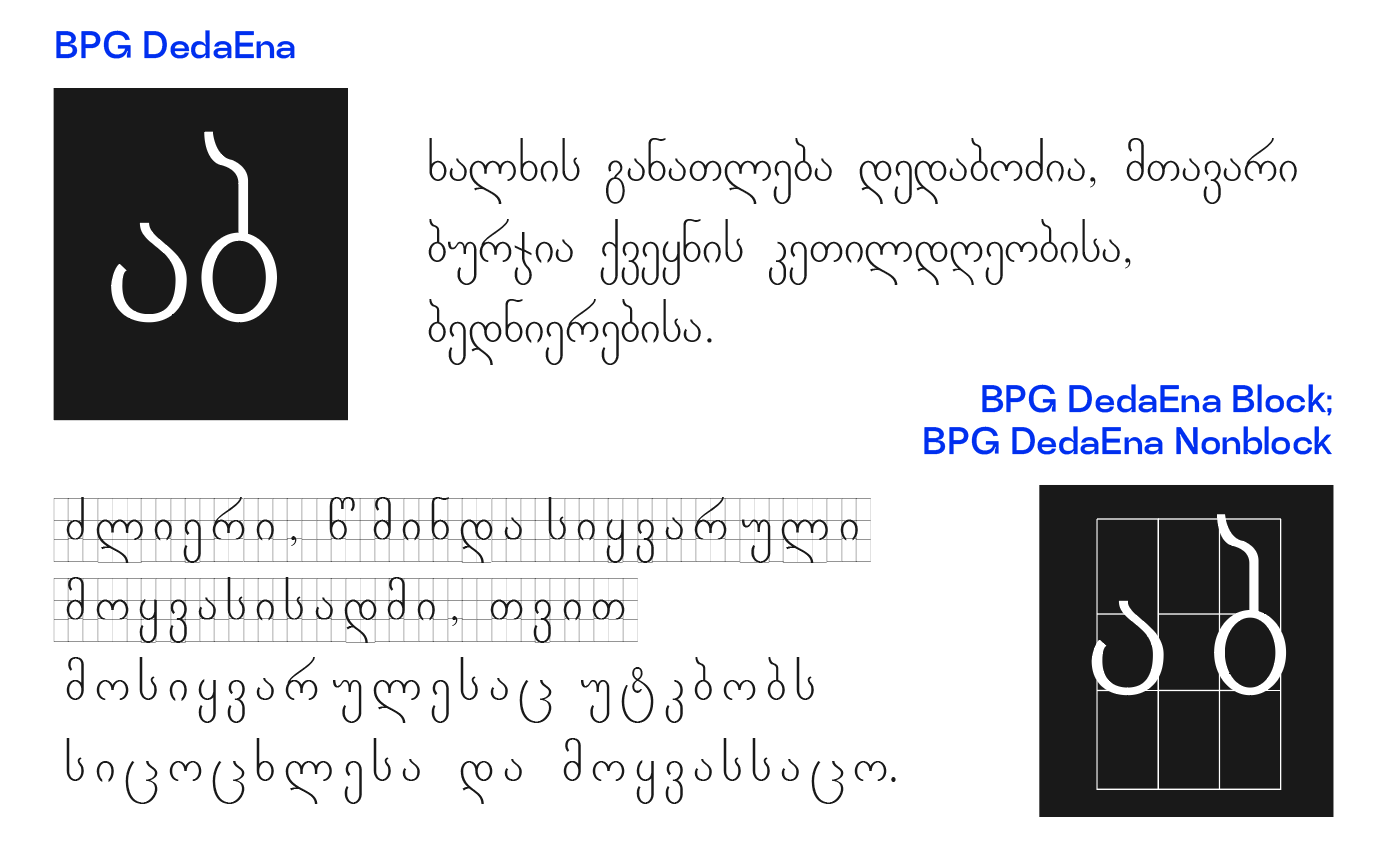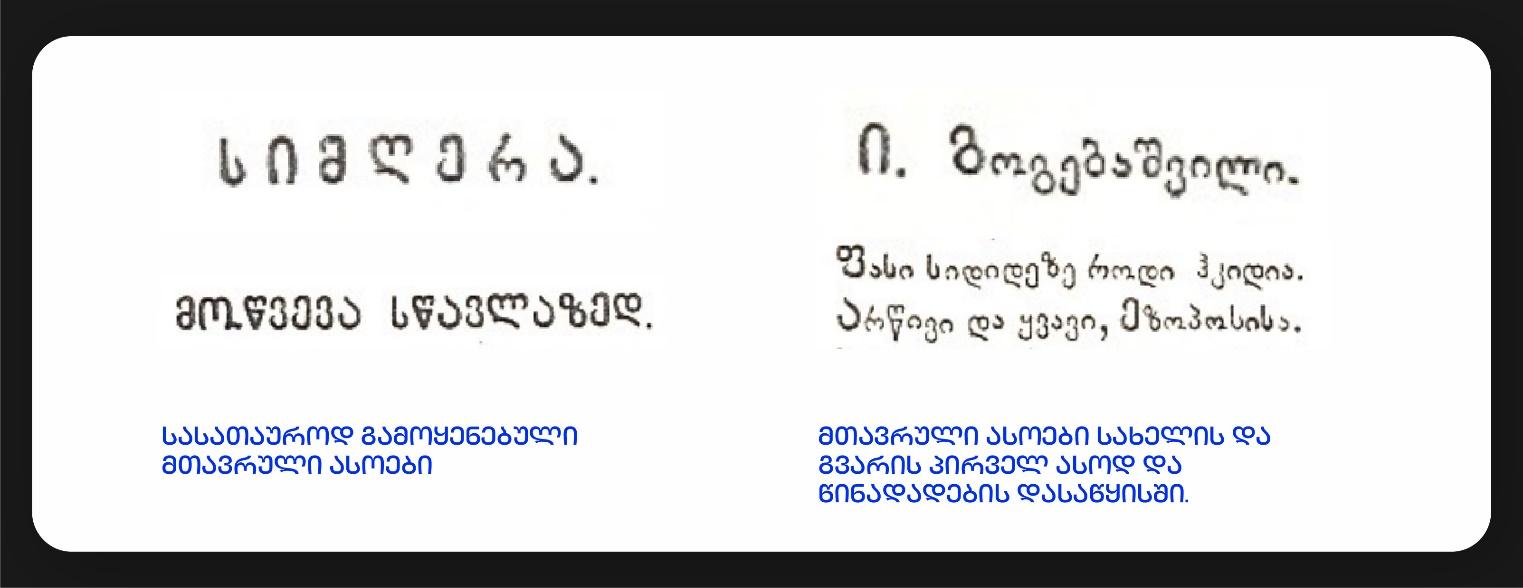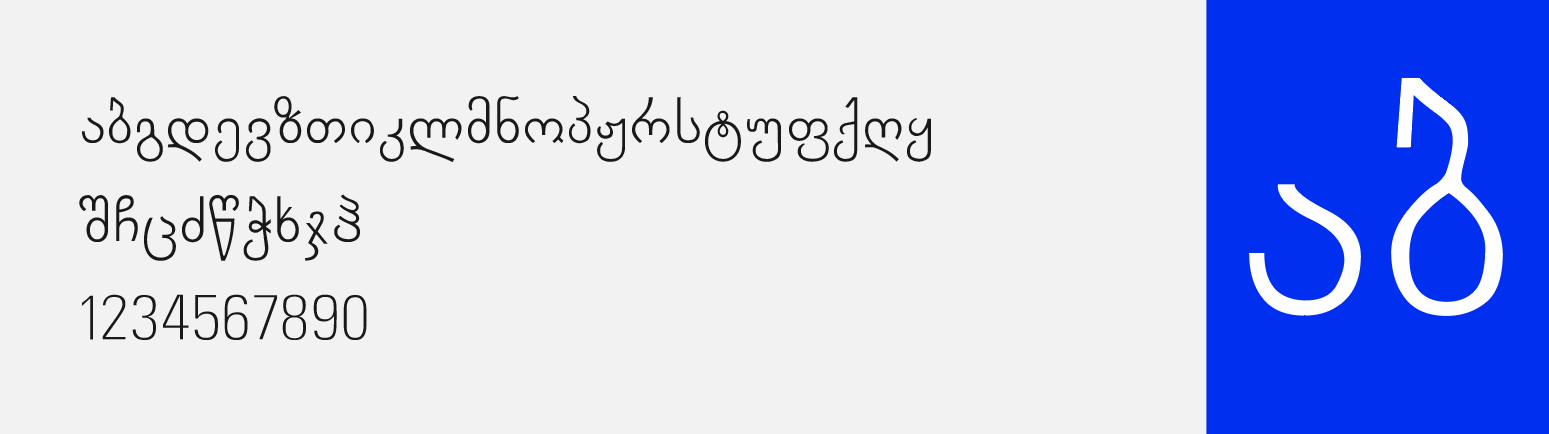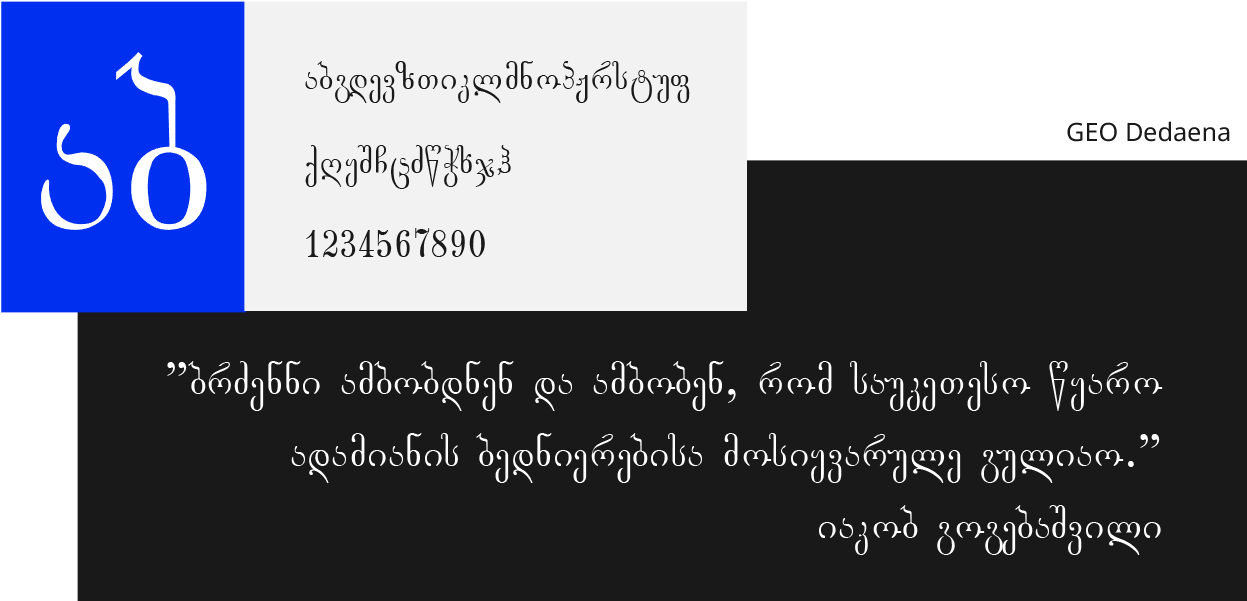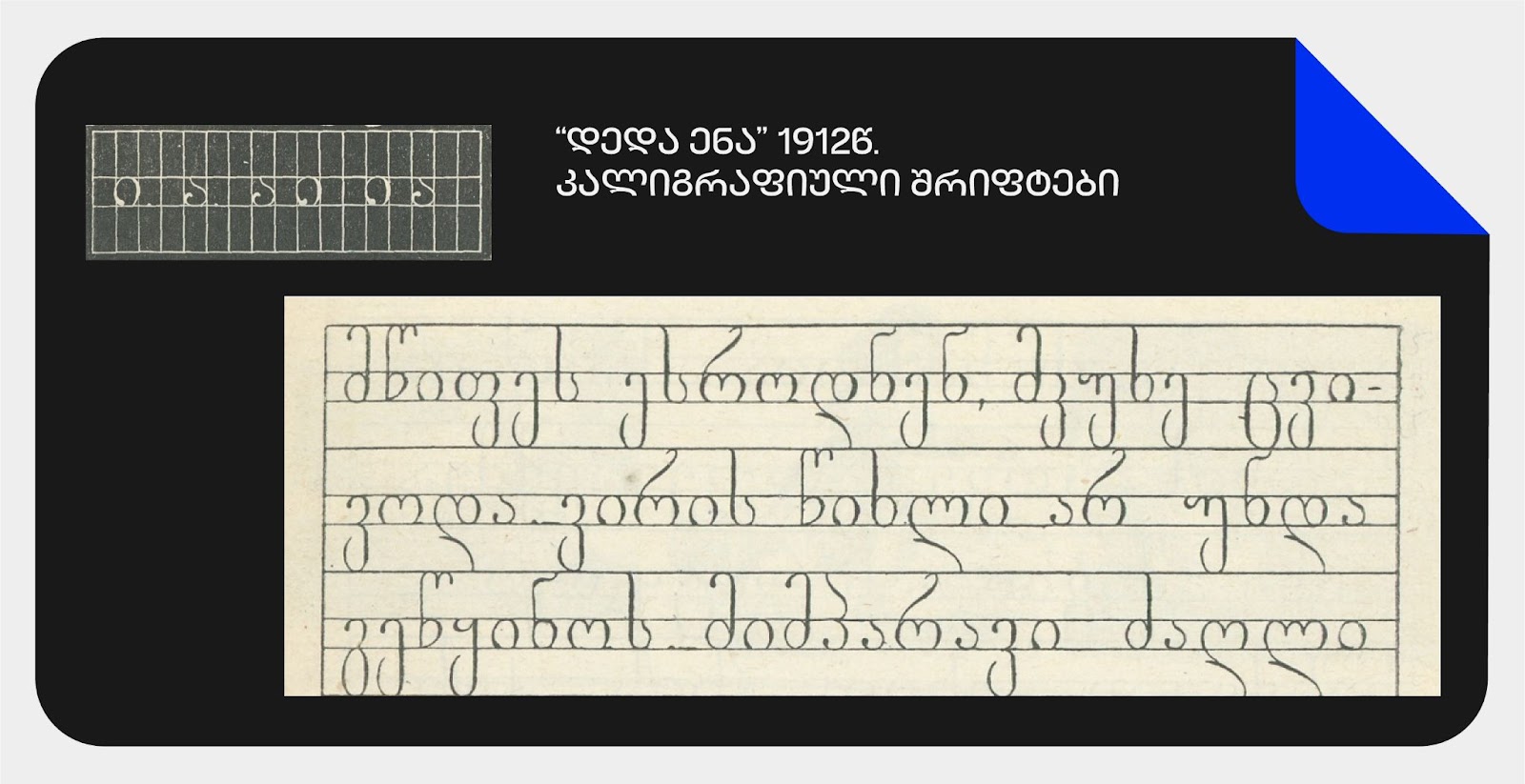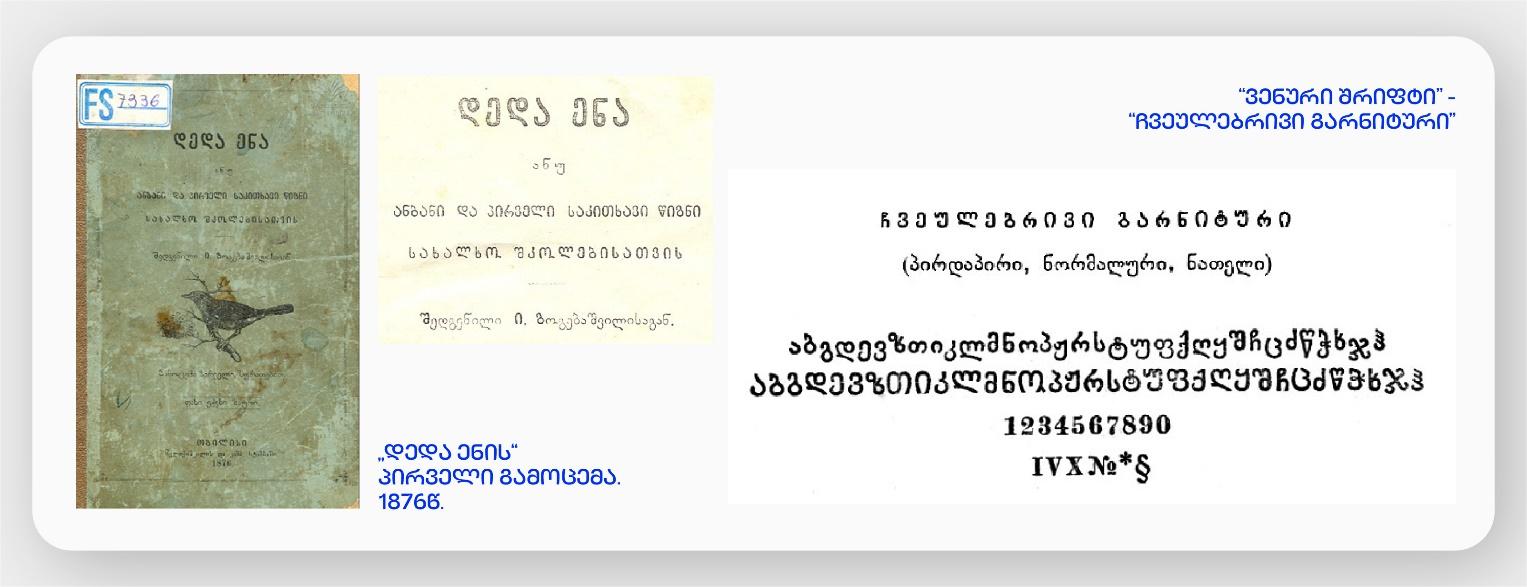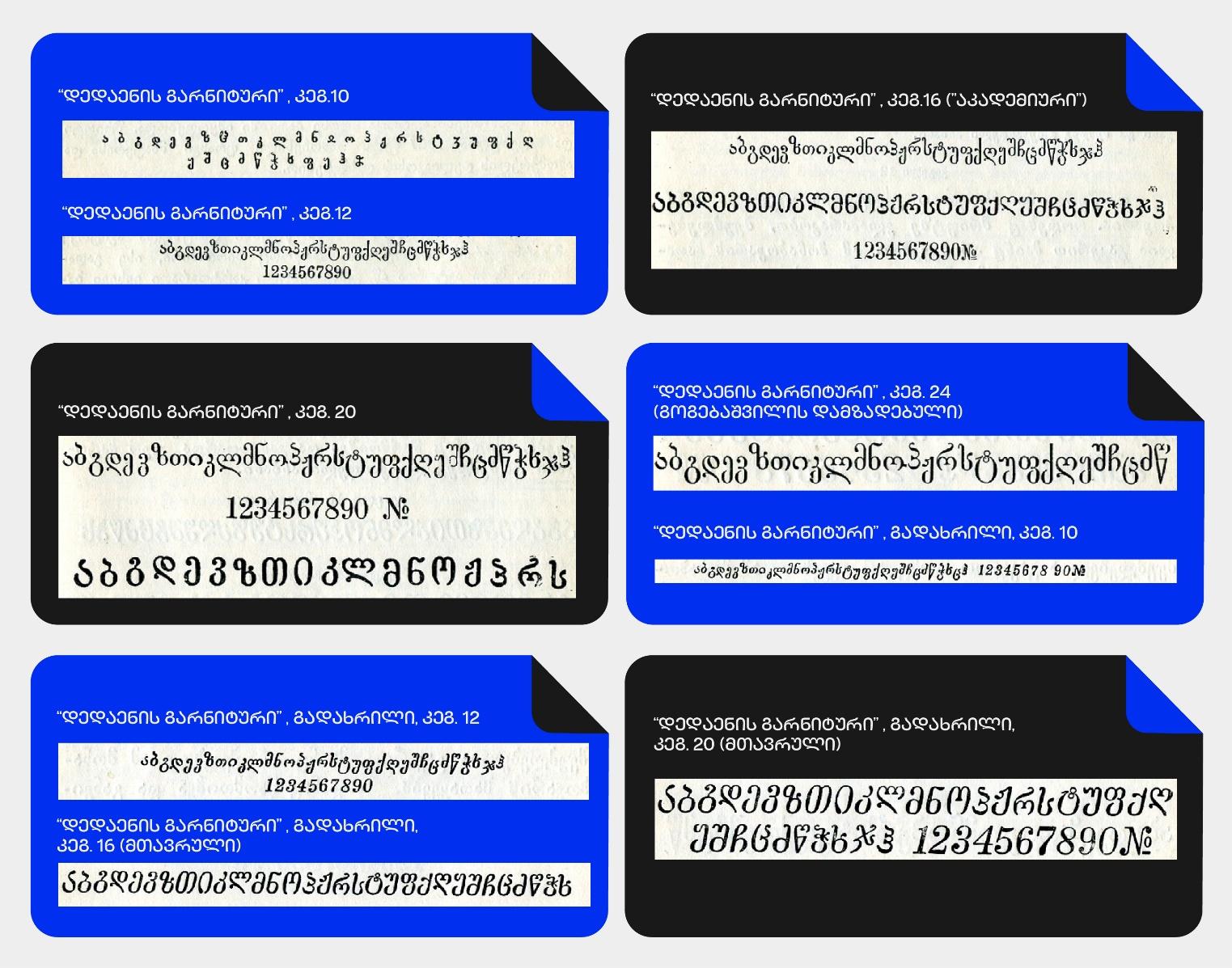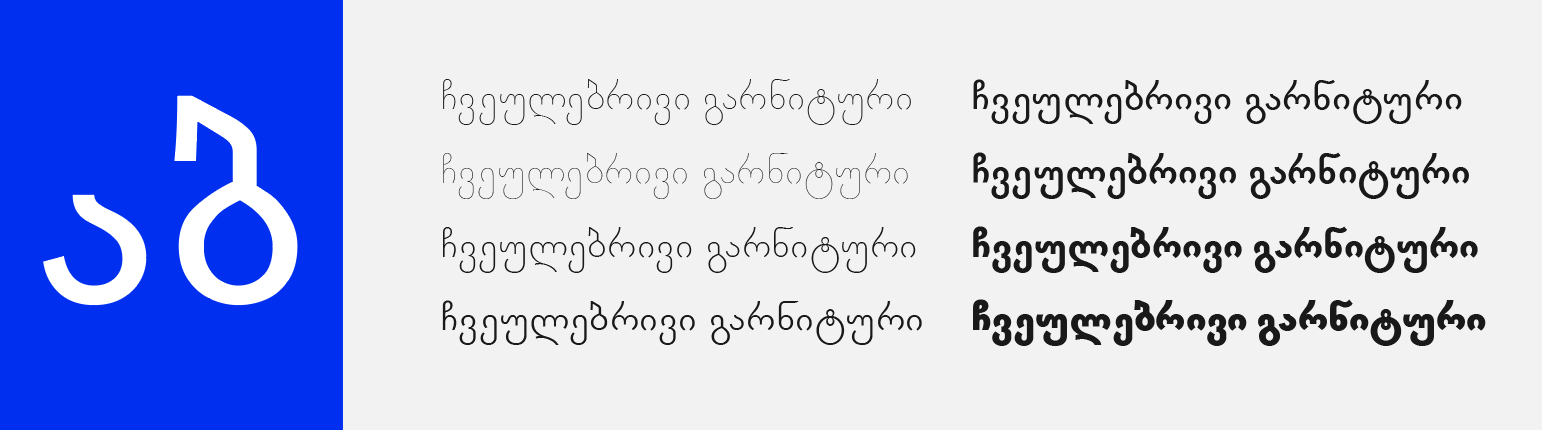
პირველი „დედა ენა“ დაიბეჭდა 1876 წელს, მელიქიშვილის სტამბაში. იმ დროისთვის სასტამბო მეურნეობა შრიფტების მრავალფეროვნებით ნამდვილად არ გამოირჩეოდა.
პეტერბურგიდან საქართველოში დაბრუნებულმა ახალგაზრდობამ ძალიან კარგად იცოდა, რამდენად მნიშვნელოვანი იყო სასტამბო საქმის გამართვა. თბილისის სტამბებში მხოლოდ პეტერბურგის აკადემიის მოძველებული და გაცვეთილი ქართული შრიფტები მოიპოვებოდა. 1863 წელს შეიკრიბა რამოდენიმე ახალგაზრდა და დააარსეს სტამბა. ესენი იყვნენ: სტეფანე მელიქიშვილი, დიმიტრი ბაქრაძე, ვახტანგ თულაშვილი და ნიკოლოზ ღოღობერიძე.
კონკურსის დახმარებით შეირჩა მიხეილ ყიფიანის შრიფტის ესკიზი. 1864წ. სტეფანე მელიქიშვილი გაემგზავრა ვენაში შრიფტის ასოების შესაკვეთად. დამზადდა ახალი მხედრული შრიფტი „ვენური“ (შემდგომში „ჩვეულებრივი გარნიტური“ ეწოდა), რომელიც ახალ ფურცელს წარმოადგენდა ქართულ ტიპოგრაფიაში: ეს იყო პირდაპირი მოხაზულობის, მარტივად საკითხავი შრიფტი, რომელმაც ქართული შრიფტი პირველად გაათავისუფლა ხელნაწერის გავლენისგან.
გოგებაშვილს შრიფტების დიდი არჩევანი არ ჰქონია, როცა „დედა ენის“ პირველ გამოცემაზე მუშაობდა. ის „ვენური“ შრიფტის მიმართ დადებითად იყო განწყობილი, „კარგ, მრგვალ და გარკვეულ შრიფტად“ მიაჩნდა. თავის სახელმძღვანელოშიც პირველად სწორედ „ვენური“ გამოიყენა.
აღსანიშნავია, რომ ამ შრიფტს ახლდა მთავრული ასოებიც. ეს იყო პირველი შემთხვევა, როცა მხედრულის მთავრული ხმარებაში შემოვიდა. „დედა ენაში“ ორი ფუნქციით გამოიყენებოდა:
დღეს მთავრულს მხოლოდ პირველი ფუნქციით ვიყენებთ, ლათინურის იმიტაციამ ქართულ ენაში ფეხი ვერ მოიკიდა.
მიუხედავად იმისა, რომ სასტამბო შრიფტებიდან გოგებაშვილს ყველაზე მეტად „ვენური“ მოსწონდა, „დედა ენის“ პირველმა გამოცემამ მაინც დაიმსახურა კრიტიკა შრიფტის მცირე ზომის გამო, რაზეც იაკობმა გაზეთ „ივერიაში“ (1881წ. № 6, გვ. 163-4) გამოაქვეყნა პასუხი:
„ანბანი, მართალია, უფრო მომსხო ასოებით უნდა იყოს დაბეჭდილი, მაგრამ ეს ნაკლოვანება ჩვენი ბრალი კი არ არის, შრიფტების სიღარიბეზეა დამოკიდებული. ხეირიანი მსხვილი შრიფტი სრულიად არ მოიპოვება ჩვენებურს სტამბებში.“
„აკადემიურ“ შრიფტზე კი, რომლისგანაც შემდგომში დამზადდა „დედაენის გარნიტური“, წერდა:
„აკადემიის ასოებში იპოება მომსხო მეთექვსმეტე ნომრის შრიფტი, მაგრამ ესეც მეტად უშნო და ტლანქია, და გარდა ამისა არ უდგება სრულიად მელიქიშვილის ჩვეულებრივს შრიფტსა, რომელიც უფრო კარგს, მრგვალ და გარკვეულ შრიფტად მიგვაჩნია.”
როგორც ვხედავთ, გოგებაშვილს შრიფტების სიმცირის გამო სხვა გზა არ ჰქონდა, იძულებული იყო თავისივე დაწუნებული „აკადემიური“ აერჩია.
„აკადემიური“ პარიზში დამზადებული შრიფტი იყო პეტერბურგის სამეცნიერო აკადემიისთვის, რომელსაც თბილისის სტამბებში „ვენურის“ დამზადებამდე აქტიურად იყენებდნენ.
გოგებაშვილმა „აკადემიურის“ კეგლი 16 გაადიდებინა და ჩამოასხმევინა კეგ.24. ამ ორი ზომის შრიფტს დაერქვა „გოგებაშვილი“.
შემდგომში ამ შრიფტის ზომები გამრავლდა, დამზადდა კეგლი 10, 12, 16, 20, 24. ამას კი 1953-56 წლებში დაემატა მთავრულები, პირდაპირი და გადახრილი (კარტოგრაფი ევსევი ბარამიძის დიზაინი), ეს ყველა სახეობა მოაქციეს ერთ დიდ ჯგუფში, რომელსაც „დედაენის გარნიტური“ დაერქვა.
დავით კოხოძის შექმნილი შრიფტი. „დედაენის გარნიტურის“ ციფრულად აღდგენილი ვარიანტი. აქვს ლათინური კოდირება (ლათინური კლავიატურის არჩევით იკრიფება ქართული ასოები).
შრიფტის ავტორია ბესარიონ გუგუშვილი, დამზადებულია BPG Infotech – ის ფარგლებში.
შრიფტი სასკოლო „დედაენაში“ გამოყენებული კალიგრაფიული შრიფტის რეპლიკაა. 3 ვარიანტითაა წარმოდგენილი: BPG DedaEna Block, BPG DedaEna Nonblock, BPG DedaEna
„ვენური“ ანუ „ჩვეულებრივი გარნიტურის“ შრიფტების რამოდენიმე რეპლიკა გვაქვს:
ფონტი შექმნილია GeoLab-ის „შრიფტის დიზაინის საფუძვლებისა და ფონტ-ინჟინერიის“ კურსის ფარგლებში.
ავტორი: ზაზა ჩუგოშვილი
მენტორი: აკაკი რაზმაძე
შრიფტის ავტორია ბესარიონ გუგუშვილი, დამზადებულია BPG Infotech – ის ფარგლებში.